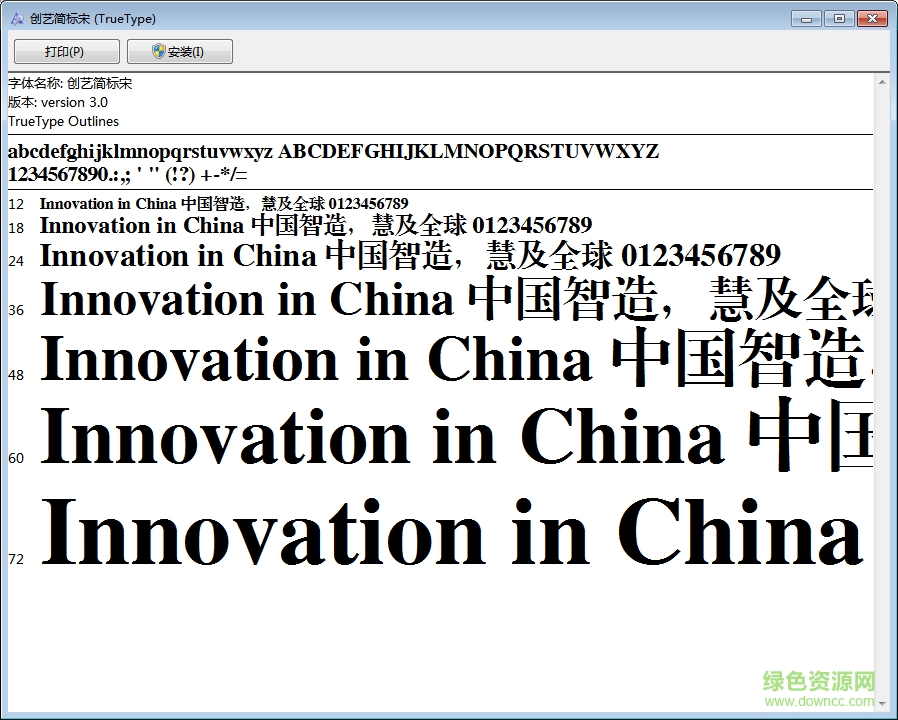
ctbiaosongsj
ctbiaosongsj 是什么字体?ctbiaosongsj.ttf字体又叫创艺简标宋,是一款看上去非常正式的宋体字体,该字体粗细变化得当,错落有致,线条舒展自如,韵意深长!
ctbiaosongsj字体特点
ctbiaosongsj是一款严谨的字体,笔画粗细分明,布局严谨且沉稳,常被用作各类书籍、报纸、杂志等标题字。用在广告设计方面能够让你的广告字体效果更佳。
ctbiaosongsj创艺简标宋